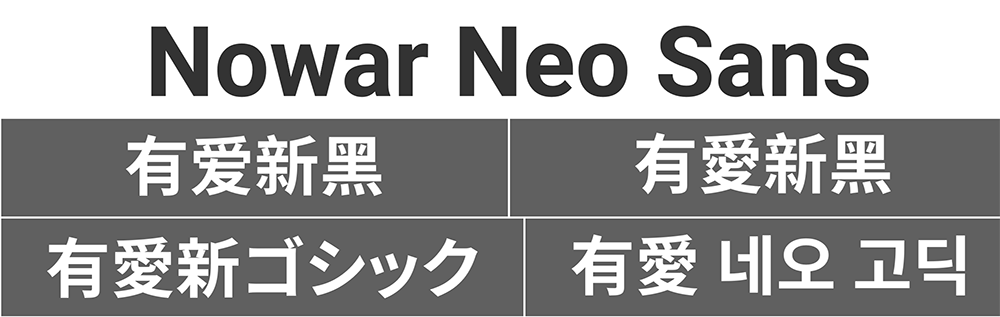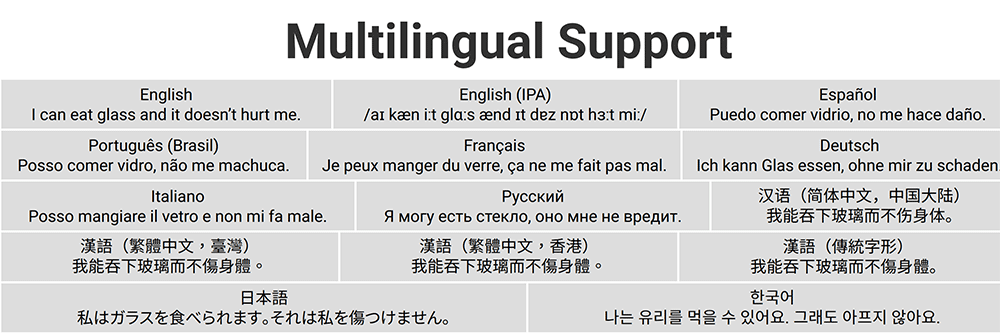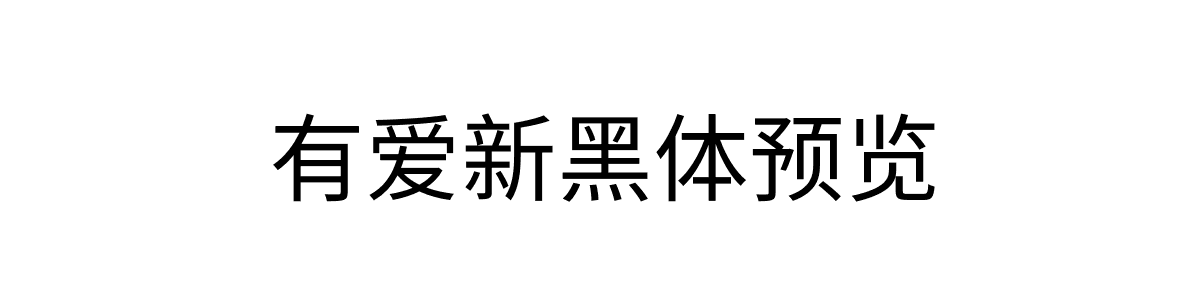
有爱新黑体 2026年3月18日 上午12:50 • 多语言字体 • 阅读 675 目录 字体预览字体风格字体下载 有爱新黑体(Nowar Neo Sans)是《魔兽世界》和《魔兽世界:经典怀旧服》的字体包,这款字体由 Noto Sans 与思源黑体整合而成,专为游戏界面使用打造,在保留思源黑体优秀显示特性的基础上,通过字形优化提升了小字号下的识别度。 字体预览 有爱新黑体 选择预设预览文本 选择预设文字 天地玄黄,宇宙洪荒。 雲騰致雨,露結為霜。 Hello, World 1234567890 !,、。!?:;“”‘’ A- A+ 自定义预览文本 选择字体字重 Light Regular Medium Bold 字体风格 作为一款面向游戏环境的无衬线字体,有爱新黑体整体清晰易读,中西文字形搭配统一协调,在游戏界面中显示稳定,适合长时间游戏阅读使用。 字体下载 有爱新黑 下载次数 99 字体类型 黑体 授权协议 OFL 授权类型 免费商用 刷新 OFL日文简体繁体韩文黑体阅读字体 赞 (0) 0 0 生成海报 相关推荐 多语言字体 有爱黑体 有爱黑体(Nowar Sans)是面向《魔兽世界》与怀旧服制作的开源内嵌字体,由 Noto Sans 与思源黑体整合而成。这款字体针对游戏界面做了专门适配,不管是任务描述还是物品说明,都能完整、准确地显示,同时也考虑到了玩家长时间游戏容易产生视觉疲劳的问题,在阅读体验上做了优化。 2026年3月29日 4850 多语言字体 快去写作业CJK 快去写作业CJK(CEF Fonts CJK)是一款完全由鼠标绘制、覆盖海量字符,专为艺术创作设计的“仿”手写风格泛CJK字体。该字体由个人开发者从2020年4月25日起,历时两年多,纯粹使用鼠标(而非数位板)逐个点画完成。 2026年1月16日 3000 多语言字体 狮尾肉丸 狮尾肉丸是一款基于思源宋体进行笔画造型改造的开源字体,对笔画的关键转折和末端进行了系统性的重塑,将宋体标志性的三角形装饰角改造为柔和的半圆形。使字体在保留宋体基本骨架的同时,注入了圆润可爱的气质,整体造型更加简明现代,版面效果清新轻快。与思源宋体一脉相承,狮尾肉丸同样提供7种字重,字符覆盖简体中文、繁体中文、韩文与日文,是真正意义上的多语言字体家族。 2026年3月14日 1151 多语言字体 有爱圆体 有爱圆体(Nowar Rounded)是专门为《魔兽世界》和经典怀旧服制作的游戏界面字体。它由 Noto Sans 和资源圆体(Source Han Rounded)结合衍生而来,既保留了思源黑体规整易读的结构,也延续了资源圆体柔和圆润的字形特点。 2026年3月29日 8320 多语言字体 狮尾加糖宋体 狮尾加糖宋体(Swei Sugar)是一款基于思源宋体进行改造的开源宋体,它专门把传统宋体太细的横笔加粗了一些,让横竖笔画粗细没那么悬殊,看着更平衡。 字体有7种字重,支持简繁中文、韩文和日文,日常排版、多语言设计都能用。 2026年3月16日 1830 发表回复 请登录后评论...登录后才能评论 提交